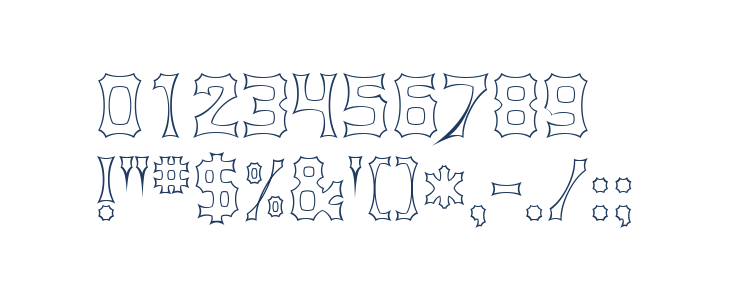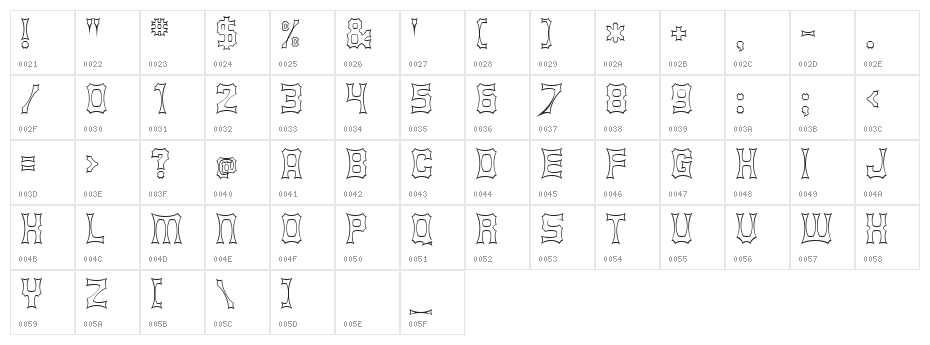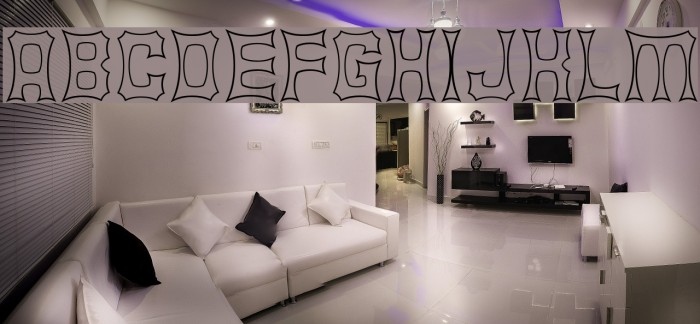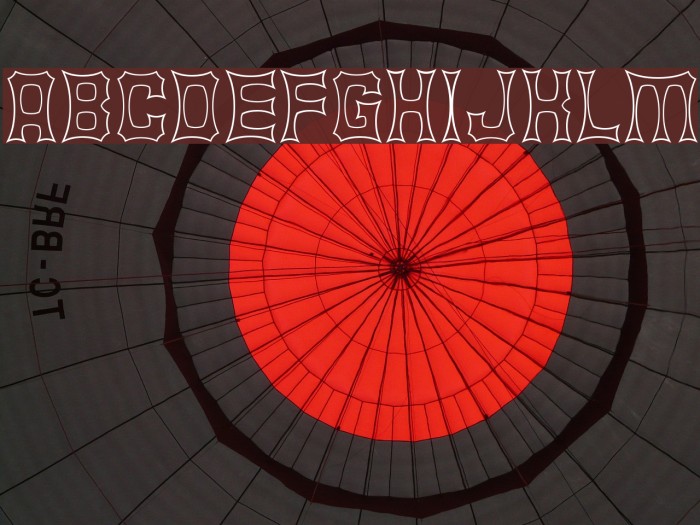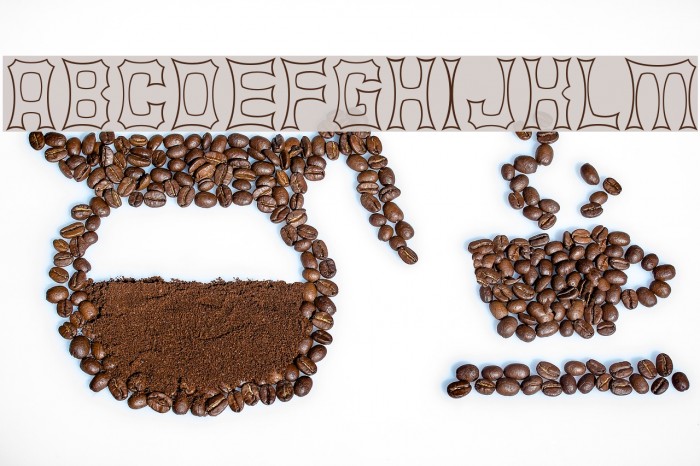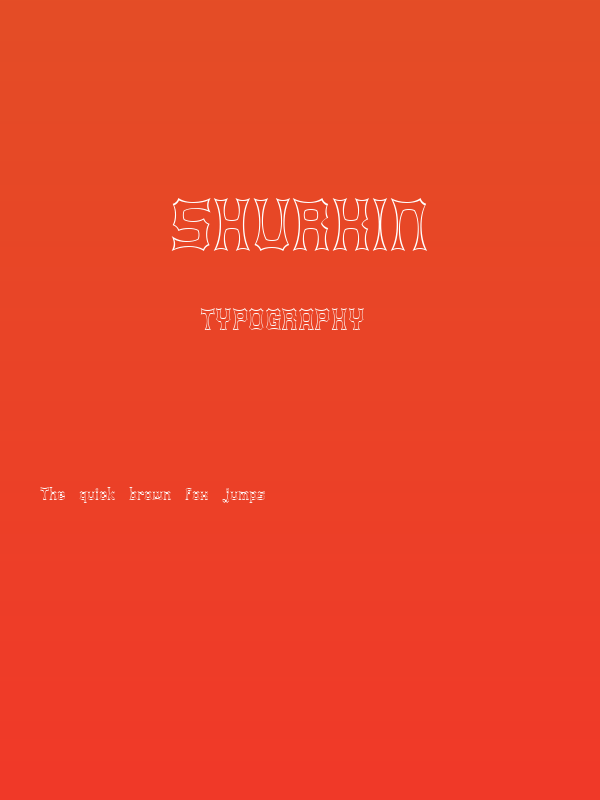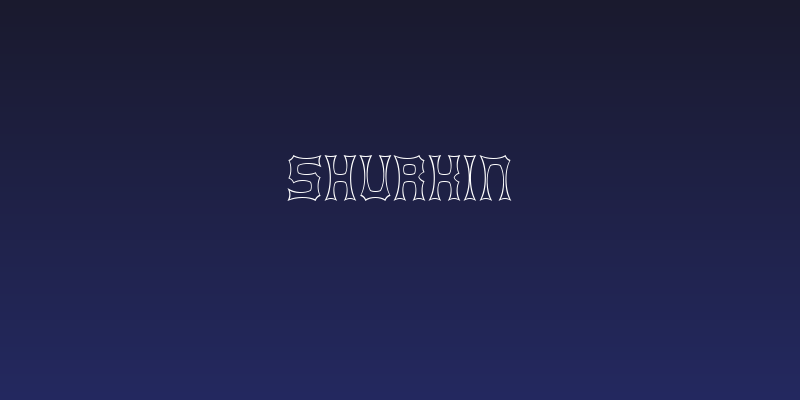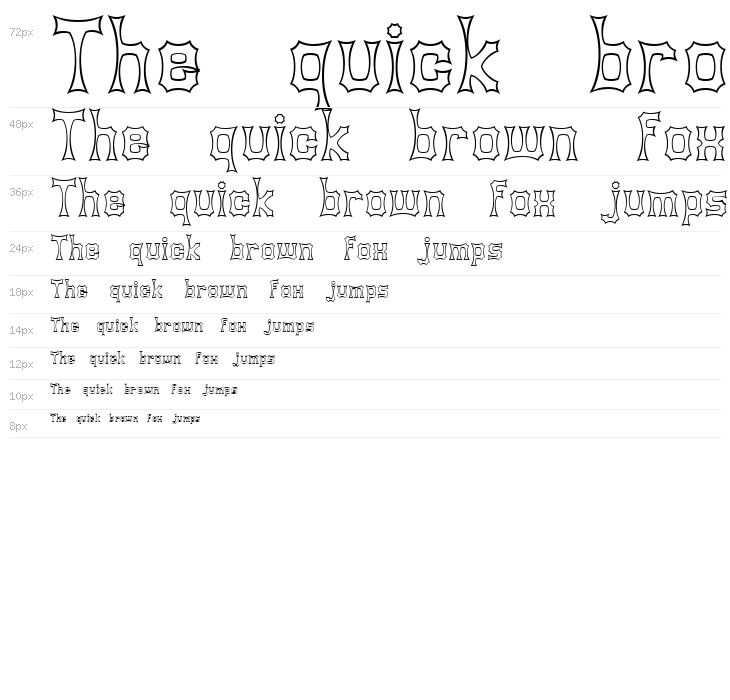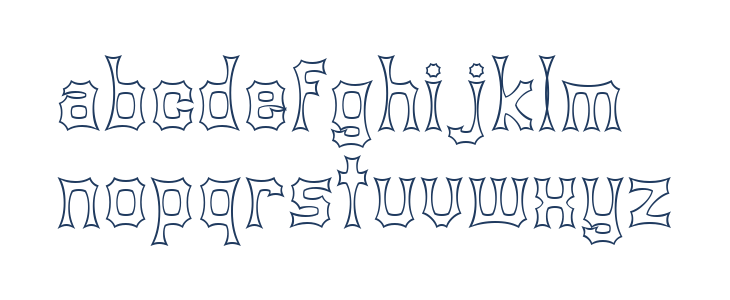
Shurkin Font
✎ Gothic
| النمط العام | Gothic, Edgy, Dramatic |
| حالة الاستخدام | Logos, Posters, Themed Events |
| مشاريع مقترحة | Perfect for Halloween-themed designs, rock band logos, edgy posters, or any project needing a dramatic flair. |